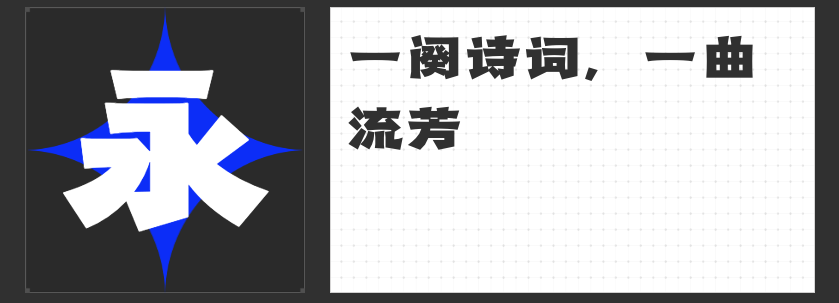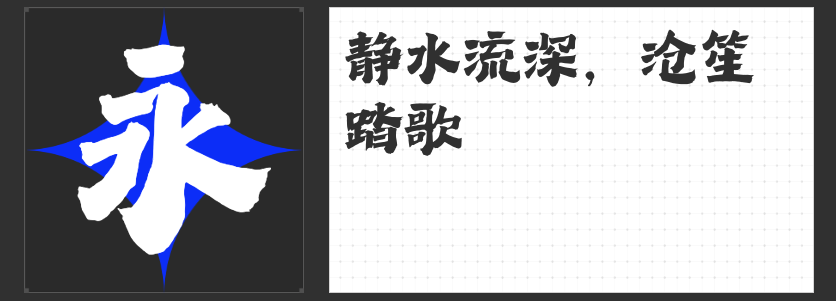
舌尖上的艺术——四款不可错过的食品宣传设计字体
在美食的世界里,除了味觉享受外,视觉体验同样重要。优秀的食品宣传海报不仅能够吸引顾客的目光,还能激发他们品尝美味的欲望。为此,我们特别精选了四款独具匠心的字体,它们各有千秋,却都能为您的食品宣传增添无尽魅力,让每一幅海报都成为一道视觉盛宴。
1.造字侠热辣隶简
“造字侠热辣隶简”是一款融合了传统隶书元素与当代审美理念的创新字体。它继承了隶书稳重典雅的特点,同时加入了更为大胆前卫的设计手法,使其具备强烈的视觉冲击力。扁宽的中宫结构与均匀分布的笔画,赋予了字体庄重威严的气息,非常适合用来突出食品品牌的高端形象或是强调产品的传统工艺价值。
2.万人字造踏歌行体
如果说“造字侠热辣隶简”是静态的威严,那么“万人字造踏歌行体”则展现了动态之美。该字体在结体上讲究方正严谨,但在笔画处理上却不失灵动活泼,既稳重又不失生机。方中有圆、刚柔并济的特质,使得这款字体非常适合用于表现食品新鲜出炉时的那种热气腾腾、香气扑鼻的效果。
3.励字造梦简 大粗
对于那些想要传递出强劲有力信息的食品广告而言,“励字造梦简 大粗”无疑是最佳选择。这款直线型字体以其棱角分明、轮廓清晰的特点著称,能够瞬间抓住观者的注意力。其简洁有力的设计风格,特别适合用于快餐、烧烤等强调快速满足食欲的产品宣传,帮助品牌在竞争激烈的市场环境中脱颖而出。
4.造字侠郝刚快乐简微黑
最后要介绍的是“造字侠郝刚快乐简微黑”,这款字体巧妙地将西方斜体的优雅与东方隶书的韵味相结合,创造出一种轻松愉快且不失平衡感的独特风格。通过112度的倾斜角度,以及笔画间富有变化的撇捺,构建出了一种流畅而富有节奏感的视觉效果。这样的字体非常适合用于冰淇淋、甜点等旨在带给人们幸福感的食品宣传,帮助消费者在第一时间感受到产品所带来的快乐情绪。
总之,这四款字体各具特色,无论是追求古典韵味还是现代简约,亦或是寻求某种特定情感共鸣,都能从中找到合适的选择。合理运用这些字体,可以大大提升食品宣传海报的艺术感染力,让美食不仅是味蕾上的享受,更是视觉上的盛宴。